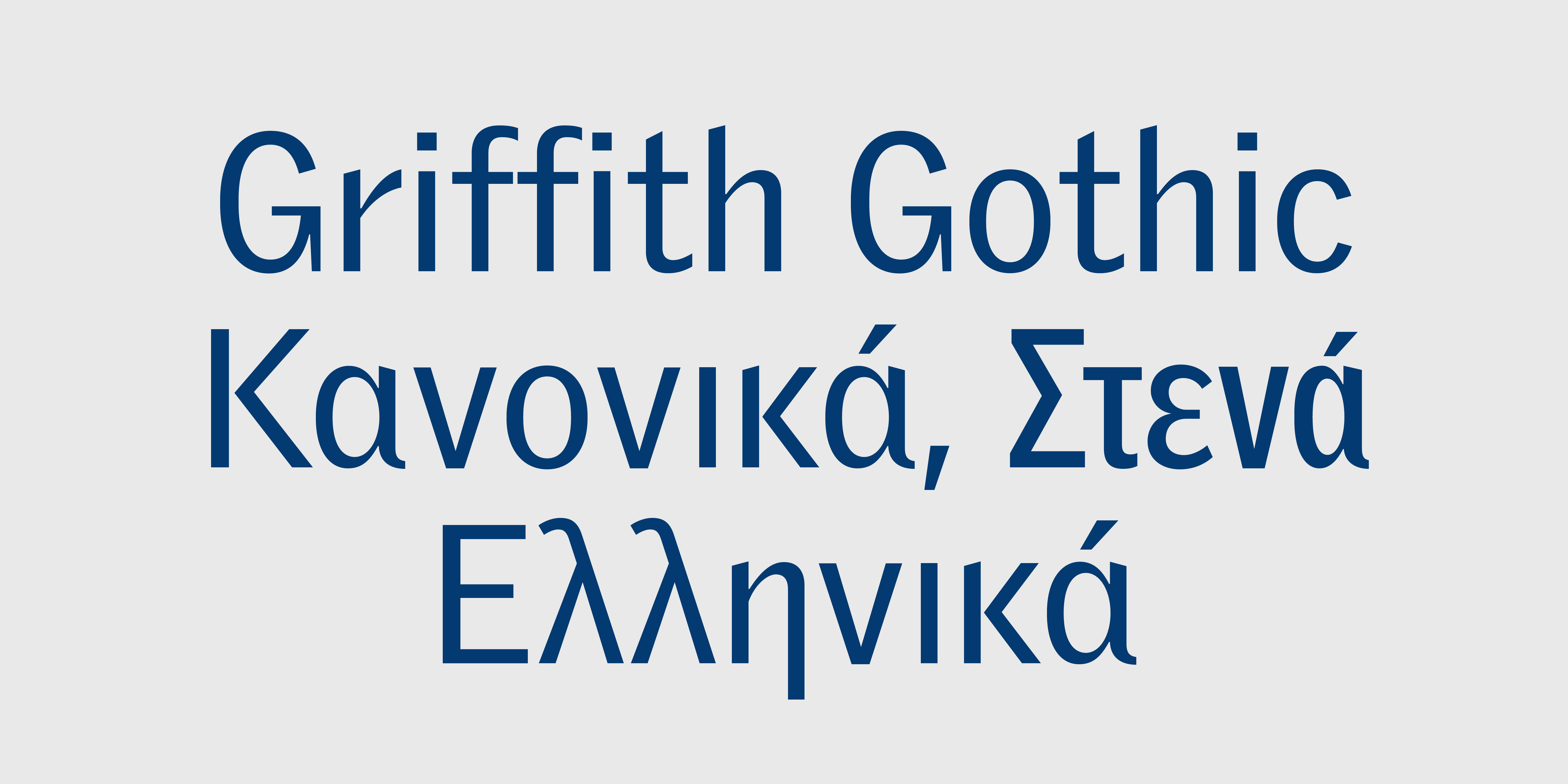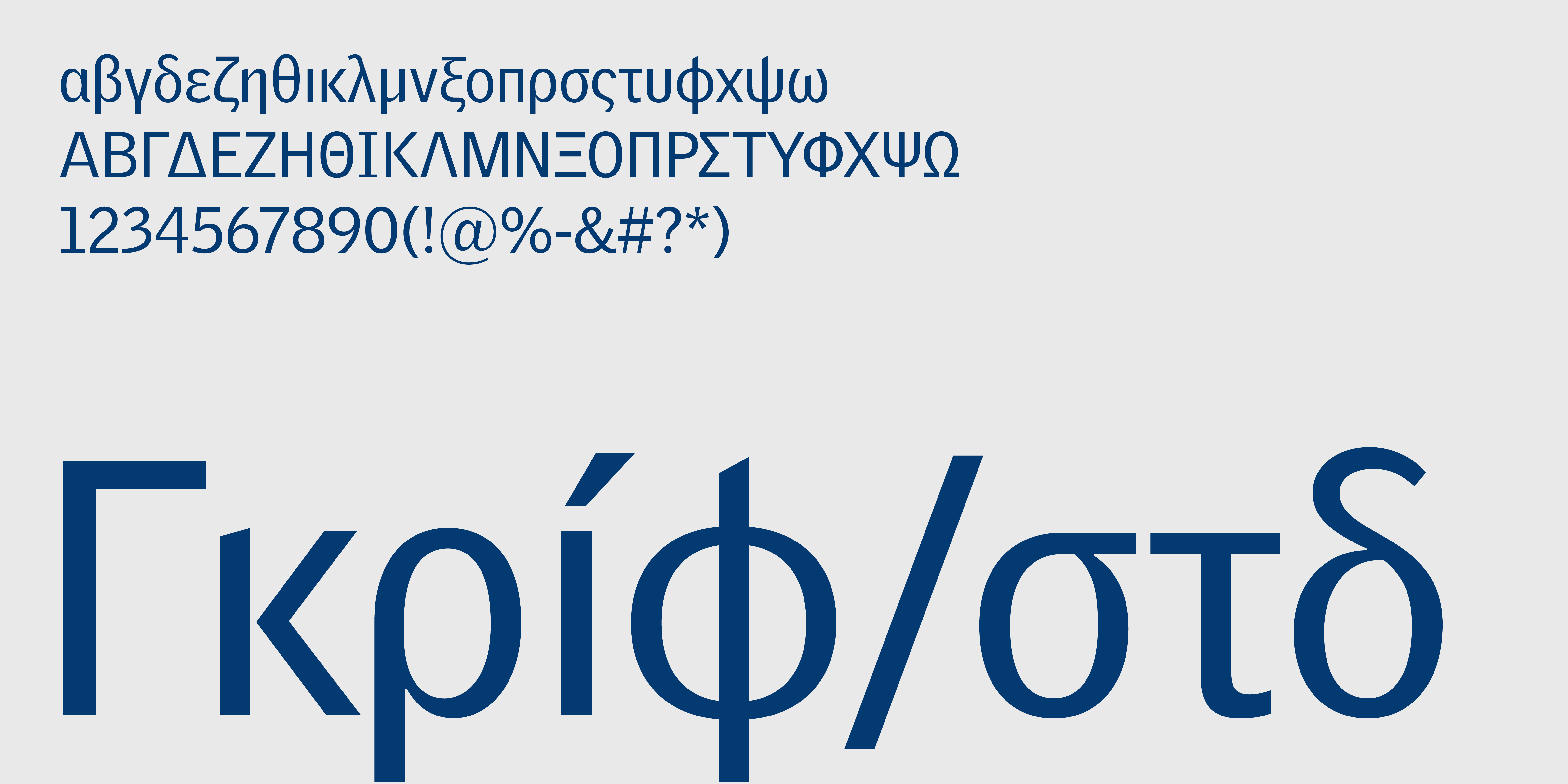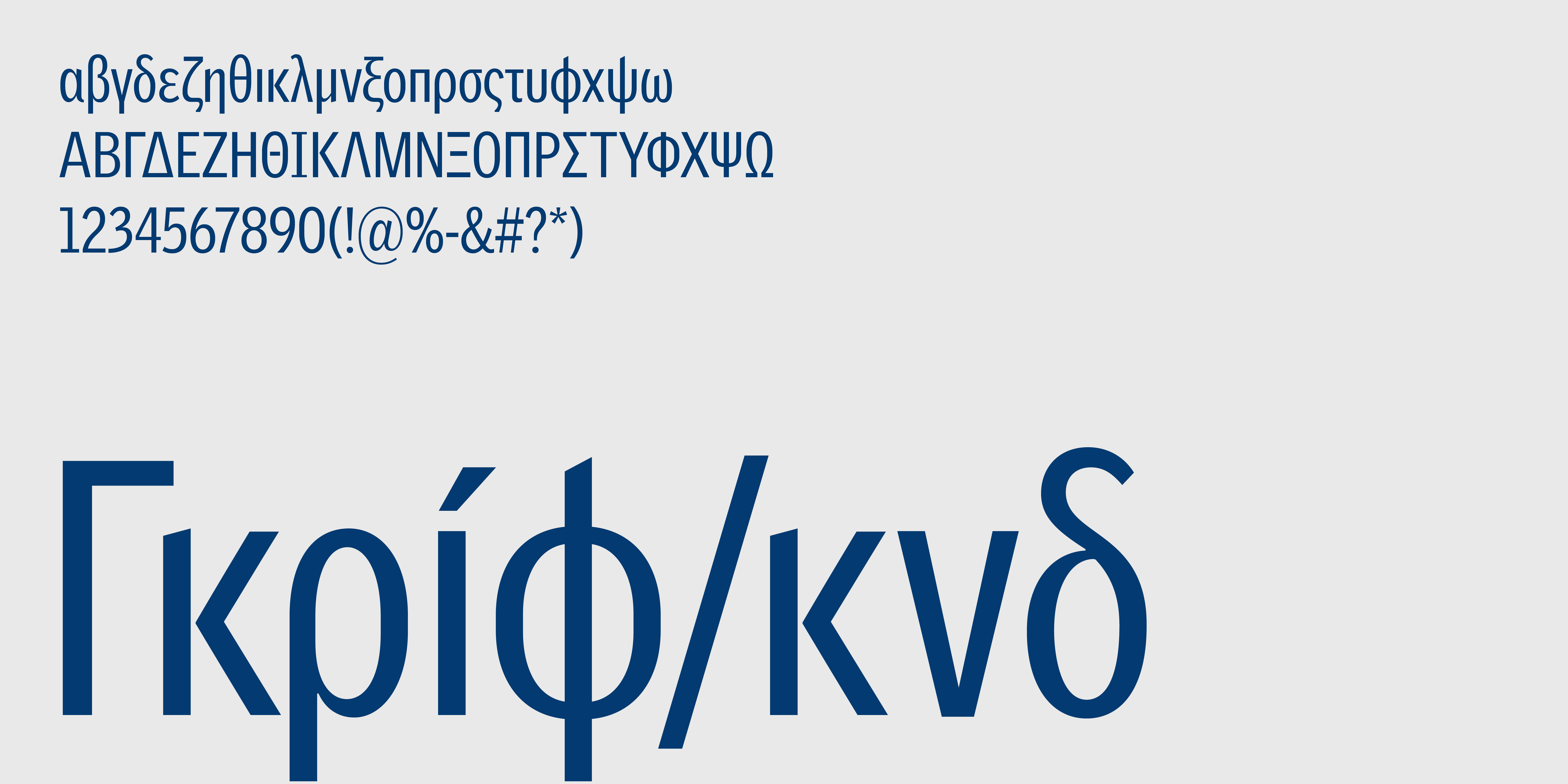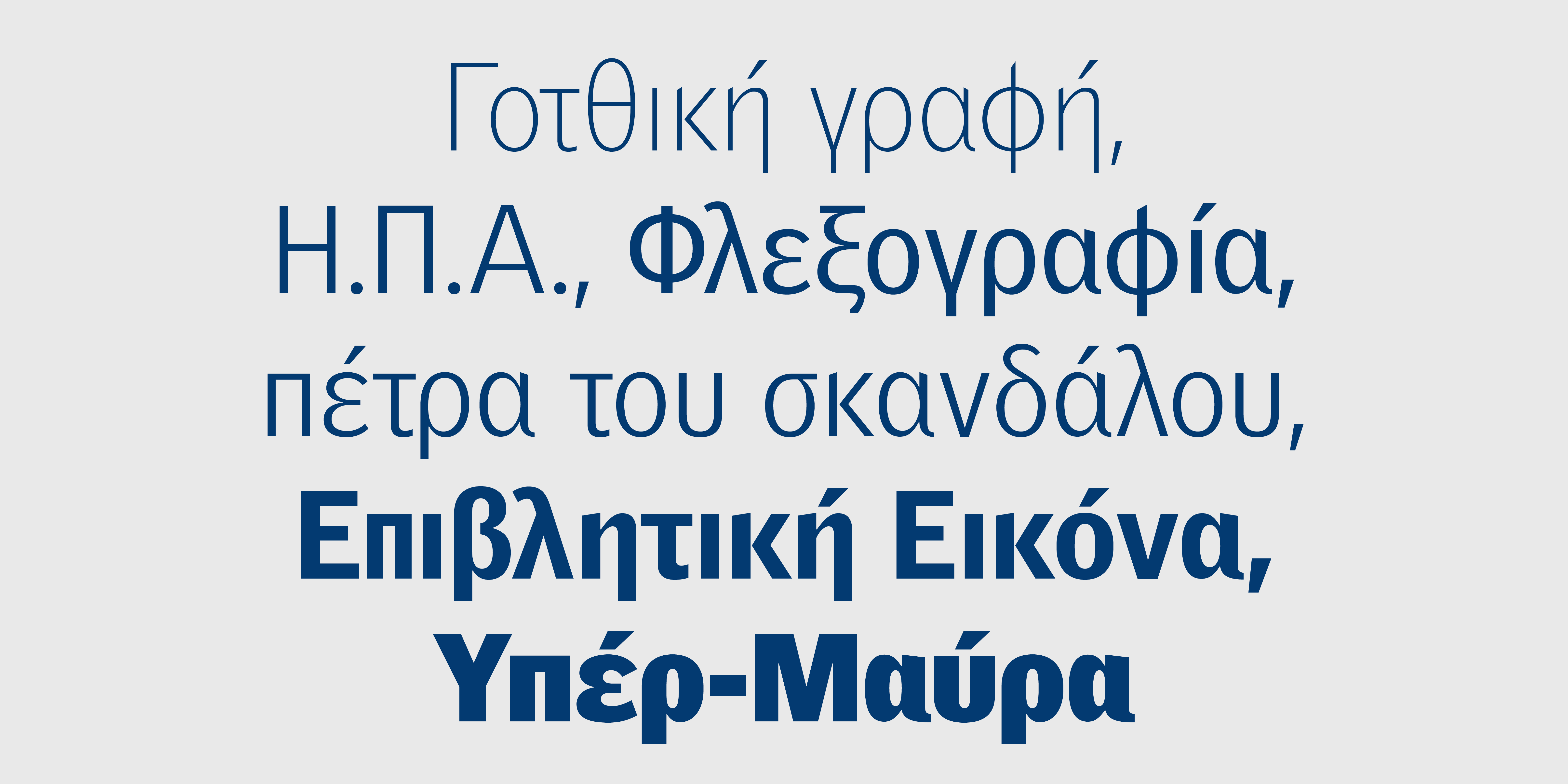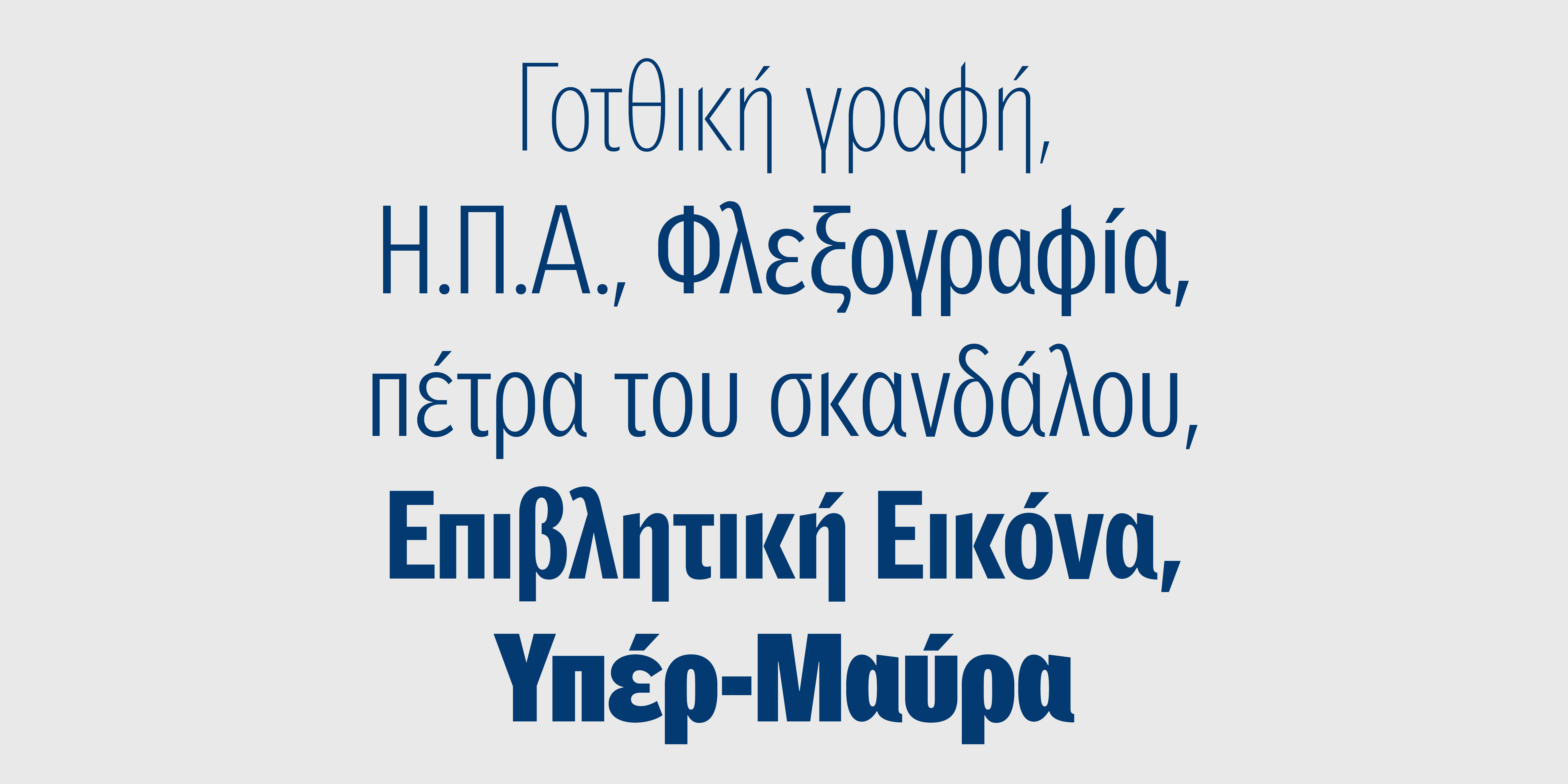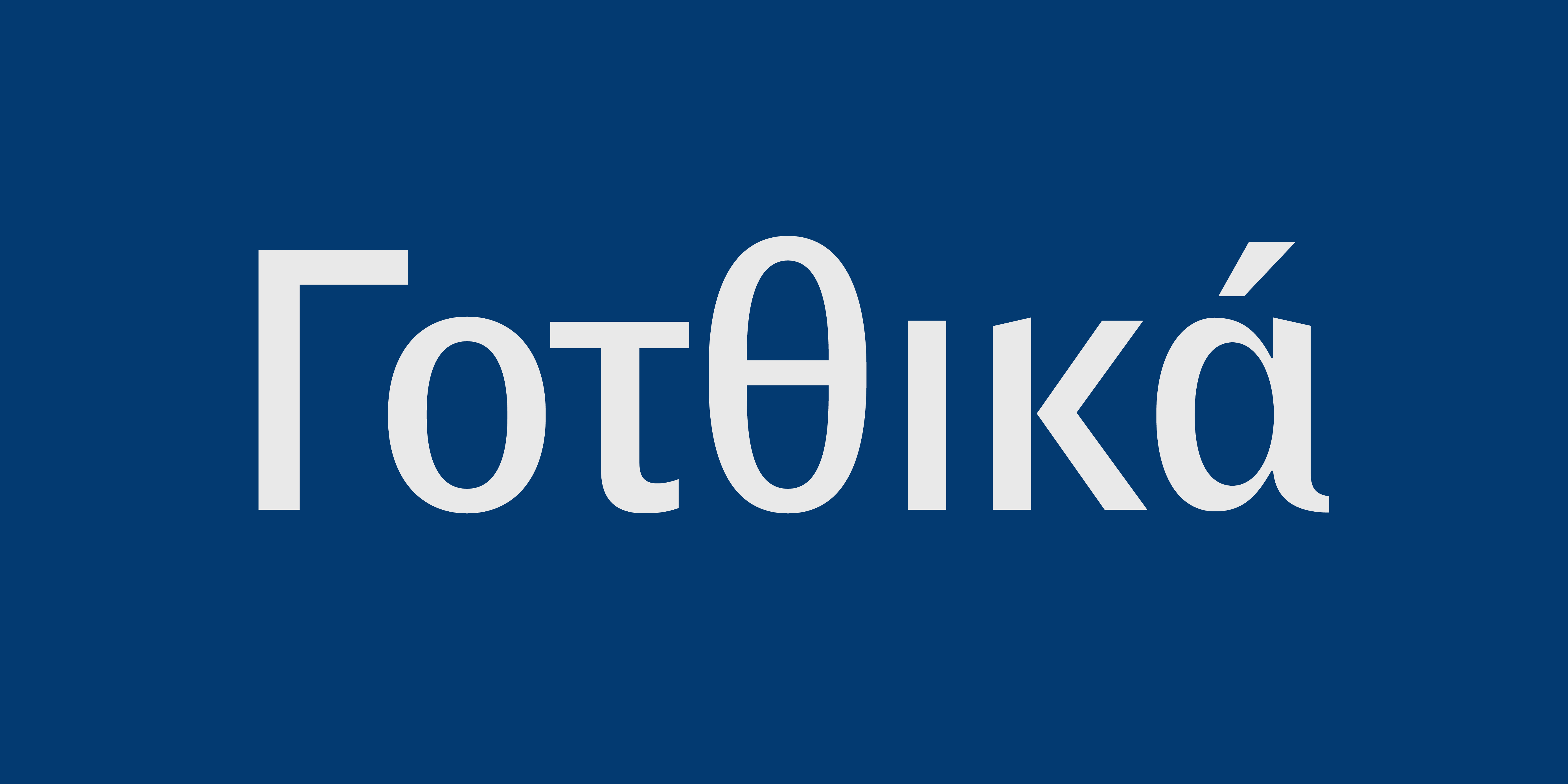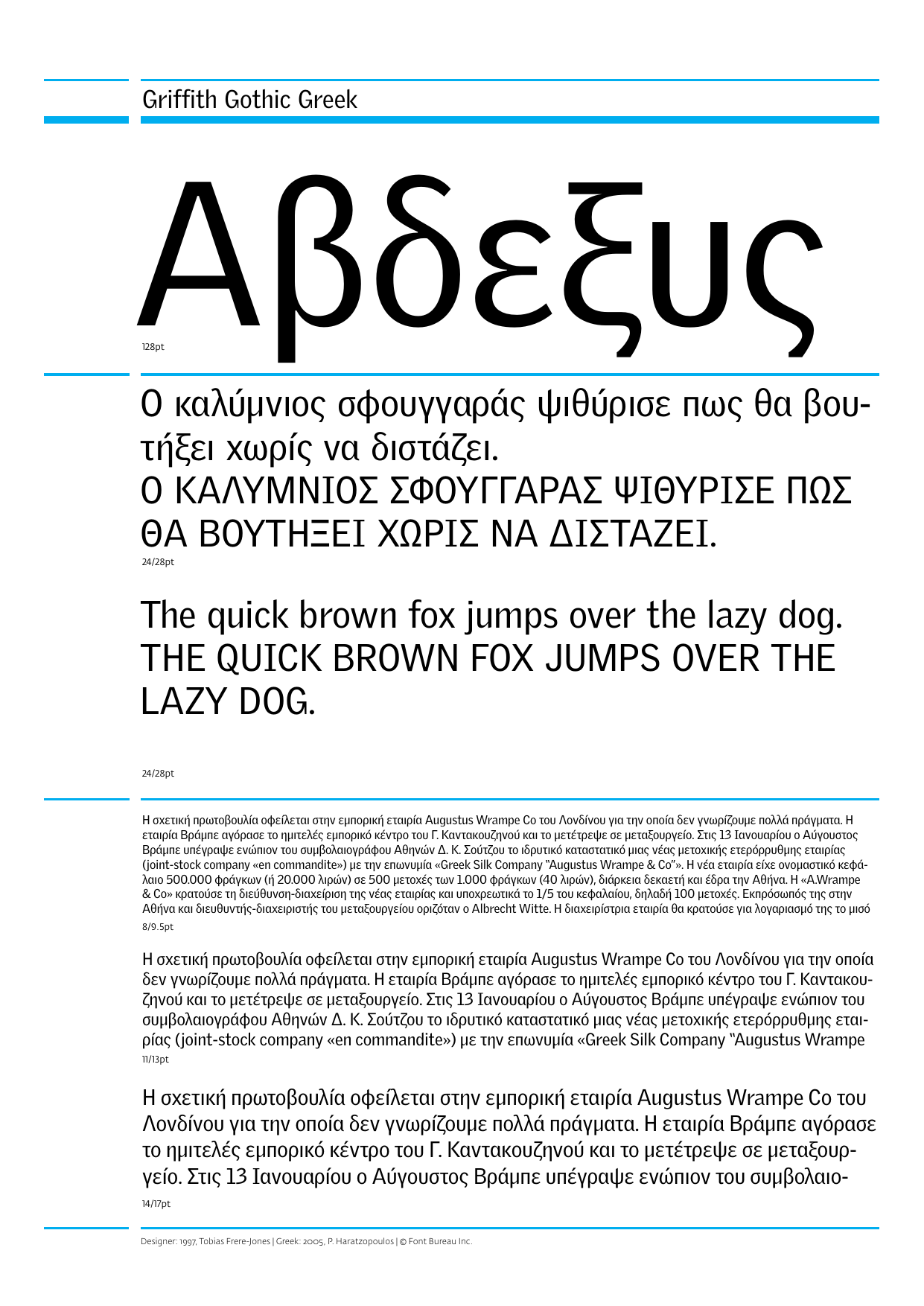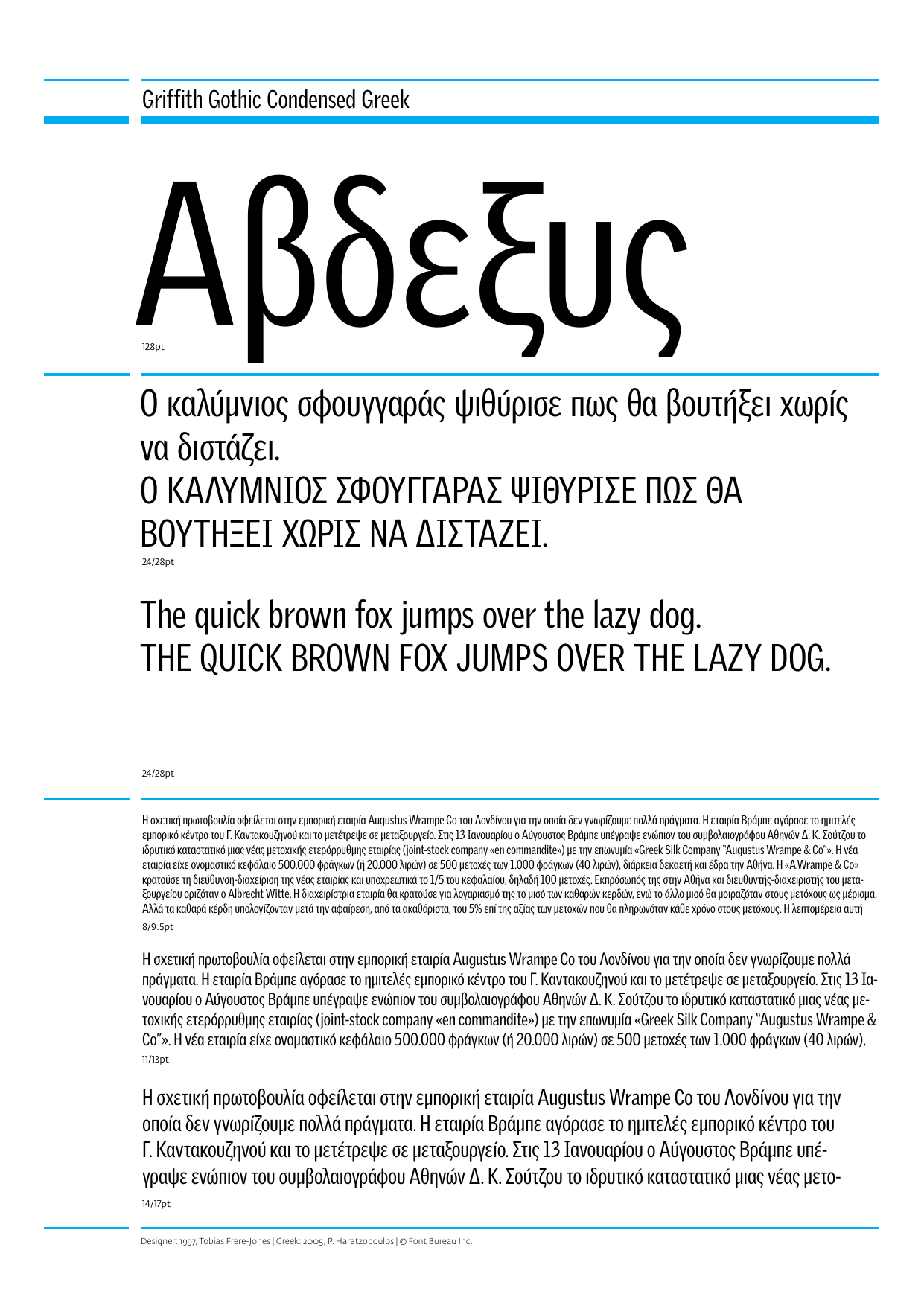
Griffith Gothic Ελληνικά Collection
Griffith Gothic Standard Ελληνικά
Thin Light Regular Bold Black UltraΗ Γραμματοσειρά είναι μία αναβίωση - επανασχεδίαση των κλασικών Bell Gothic του Chauncey Griffith. Ο Tobias Frere-Jones σχεδίασε έξι βάρη από το Thin έως το Ultra ενώ οι πλάγιες και στενές παραλλαγές προστέθηκαν για να ολοκληρώσουν αυτήν την εξαιρετικά ευανάγνωστη οικογένεια γραμματοσειρών. Ελληνική έκδοση Παναγιώτης Χαρατζόπουλος.